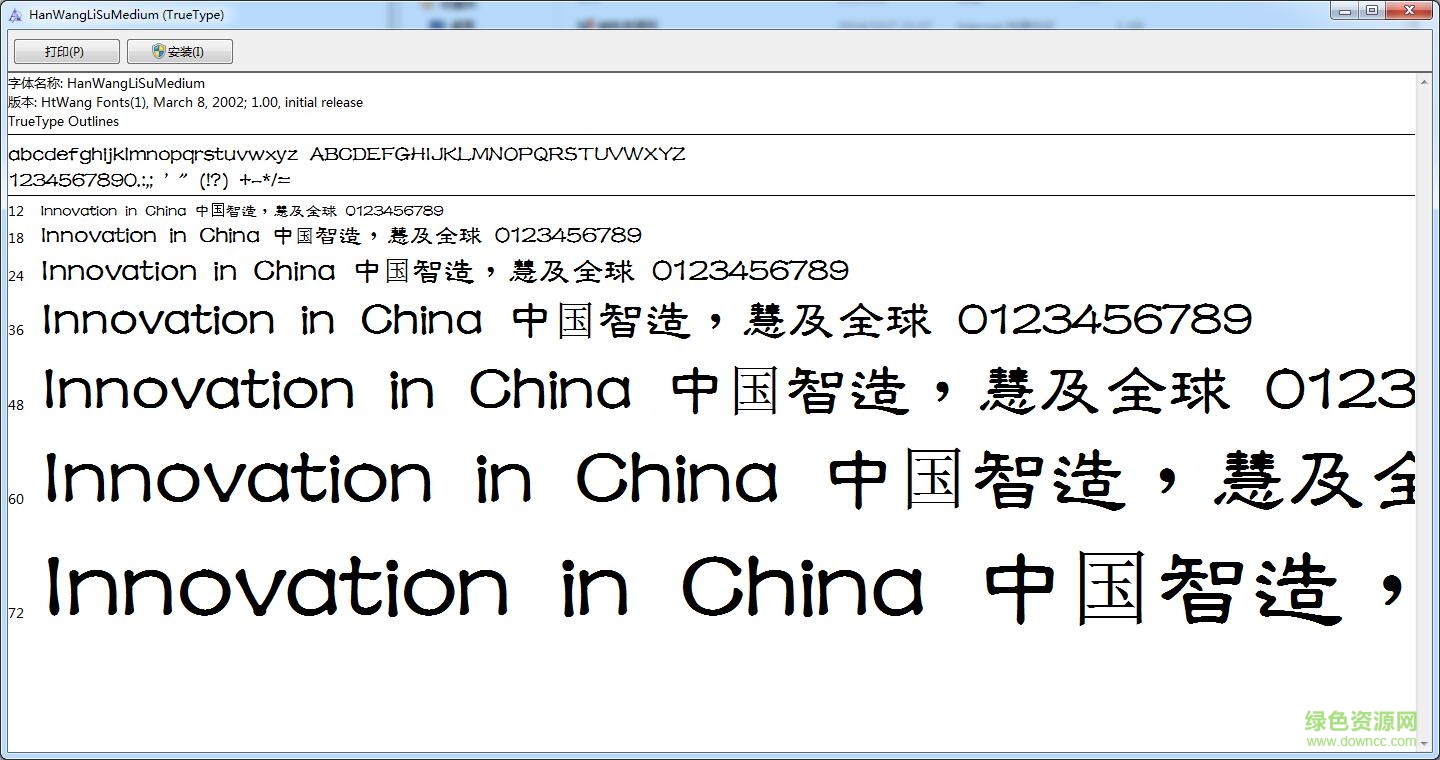
王漢宗中隸書簡(jiǎn)體是一種用途非常廣泛的免費(fèi)字體!這款字體多用于美工設(shè)計(jì)、雜志排版等方面。需要的朋友可以來(lái)本站免費(fèi)拿走!
王漢宗中隸書簡(jiǎn)字體是一款偏美工設(shè)計(jì)的字體。該字體樸茂工穩(wěn)、靈秀清麗、結(jié)體嚴(yán)整,而且字體庫(kù)完整!是一款很不錯(cuò)的字體素材。歡迎大家來(lái)綠色資源網(wǎng)下載使用。